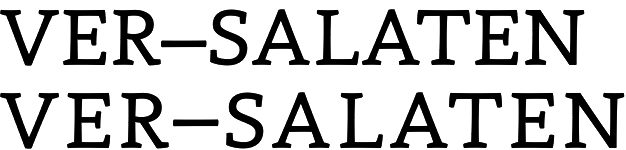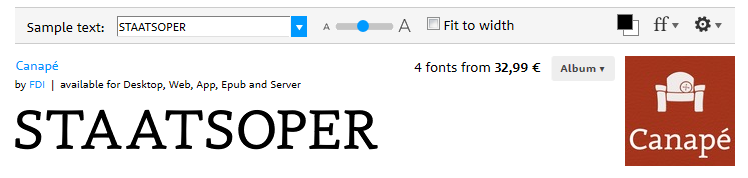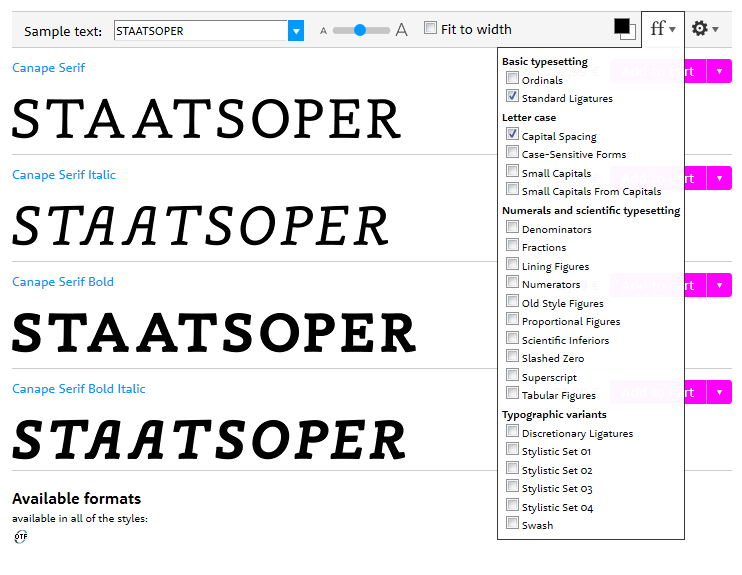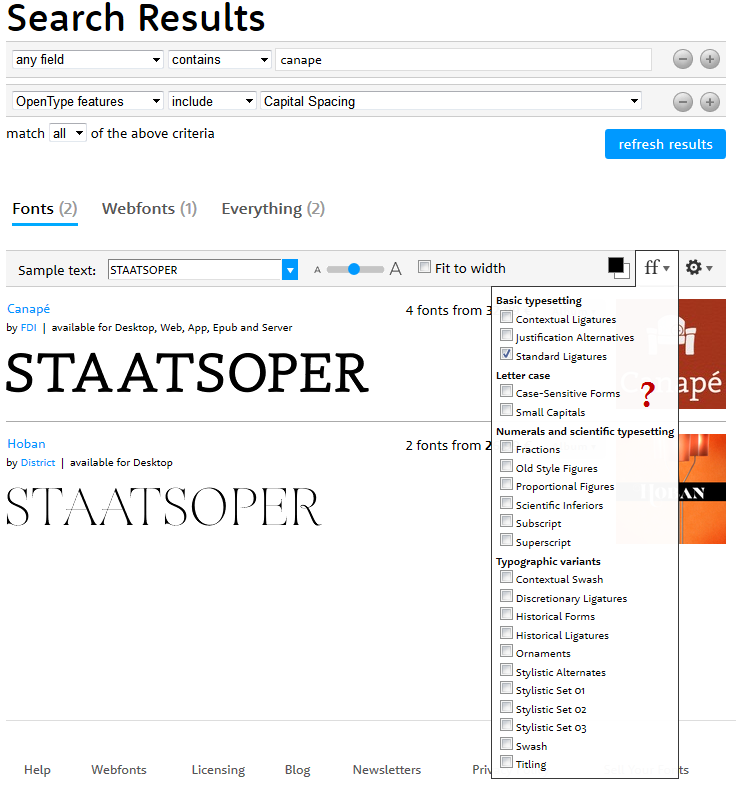
Fonts mit extra Versal-Schnitt („all caps“) – gibt’s sowas ?
Ihr werdet mir sicher zustimmen, dass das feinfühlige Ausgleichen von Versalzeilen heutzutage nahezu nirgends mehr praktiziert wird – sei es aus Nichtkönnen oder Nichtkennen. Ich habe den Eindruck, dass sich die Herren und Damen „Designer“ alltäglich damit begügen was aus dem Font herauspurzelt, wenn man Shift gedrückt hält.
Umso mehr frage ich mich, ob es bei Fonts, bzw. Fontfamilien, neben Kapitälchen-Schnitten* nicht eigentlich auch Schnitte gibt, die ausschließlich die Versalien beinhalten, dafür aber schon so zugerichtet, dass es im Allgemeinen gut ausgeglichen aussieht, wenn man damit schreibt.
Ich habe mal versucht nach so etwas Ausschau zu halten: also entweder gibt es keinen einzigen solchen Font auf diesem Planeten, oder aber mir fehlt die richtige Vokabel nach der ich suchen müsste.
Kann mir da jemand weiterhelfen?
Hättet ihr eigentlich sonst noch andere Ideen, wie man Schriftverwender in ihrer schnellebigen Alltagspraxis beim Setzen Schreiben von optisch ansprechenden Versalzeilen unterstützen könnte? Wäre es bspw. sinnvoll das als Unterschneidungspaare per OpenType-Feature in die Fonts einzubauen?
* = die leider auch viel zu oft schlecht zugerichtet, bzw. ausgeglichen sind
Die Frage impliziert, dass ein Font mit Groß- und Kleinbuchstaben nicht für Versal-Satz vorbereitet wird oder gar werden kann. Dem würde ich so nicht zustimmen. Schon ein herkömmlicher Font kann beliebige Kerning-Paare ausschließlich für Versalien bereithalten. Dazu braucht mal also keinen reinen Versalfont.
Bei OpenType-Fonts hat man dann sogar noch mehr Möglichkeiten. Hier gibt es ja bei der Umstellung auf Versalsatz ein eigenes OpenType-Feature, in dem sich die Laufweite anpassen lässt, Zeichen wie Klammern und Bindestriche verschieben lassen usw. Und das Title-Case-Feature tauscht notfalls sogar Buchstaben aus und ersetzt sie durch solche, die speziell für »Schau-Versalsatz« bestimmt sind.
Letztlich kann also jeder »gute« Font auch automatisch gut im Versalsatz aussehen. Das ist einfach eine Frage des Aufwandes, den der Typedesigner betrieben hat. Einen Spezialfont braucht man dazu nicht.
Man könnte die Frage ja umdeuten auf "welche Fonts machen sich die Mühe, Versalien nochmal für Versalsatz sauber anzugleichen, statt die Gemischtsatz-Werte zu verwenden?"
Anpassungsstufen können sein:
0) Gar nix, Versalien laufen so, wie sie für den Gemischt-Einsatz zusammen mit Minuskeln gebraucht werden
1) Versal-Kerning: Über Kerning wird sauber ausgeglichen, was aufgrund der Gemischt-Metrik ungut aussieht. Das ist viel Handarbeit, die der Schriftgestalter dem Setzer abnimmt.
2a) Opentype-CPSP-Feature "simpel gestrickt": Das CPSP-Feature addiert zu allen Versalzeichen einen festen Wert dazu (= wie Laufweitenerhöhung im Satzprogramm)
2b) Opentype-CPSP-Feature "verbessert": jedes Versalzeichen wird im CPSP-Feature gesondert betrachtet und ein passender Wert dazugegen
3) Opentype-CASE-Feature: verschiedene Satzzeichen (Klammern, Striche, ...) werden vertikal neu positioniert oder durch Sonderformen ersetzt, um besser zu Versalien zu passen.
4) Opentype-TITL-Feature: Es werden für den Titel-Versalsatz eigens gezeichnete, detailreichere Glyphen verwendet und die haben natürlich auch passende Metrik und Kerning.
Mein Canape Serif hat z.B. 1, 2a und 3 integriert, meine Tierra Nueva 1, 3 und 4.
Mal eine Verständnisfrage ...
Gibt es, wenn man es "schön" machen will, Unterschiede im Abstand für die Fälle
- durchgehender Versalsatz (VORDERRAD)
- einzelne zusammentreffende Großbuchstaben im Mischsatz? (StVO)
... hier bspw. bei VO?
Wenn gleich, könnte man ja stark vereinfacht den Platz nach links bei Großbuchstaben etwas größer machen, wie er für VO richtig passt. Dann bräuchte man nur was für die Kombi Kleinbuchstabe vor Großbuchstabe, bspw. tV oder in McIrgendwasm wo man dann ggfs. global (wenn das geht in OT?) den Zusatz wieder abzieht ...
Dann sähe das bei nicht-OT-fähigen Programmen meistens "schön" aus, außer für die wohl selteneren tV & Co.?
Dann sähe es in nicht OT-Programmen an der Linken Kante des Satzspiegels nicht schön aus, da dann alle Worte, die mit großen Buchstaben beginnen dann eingerückt sind.
Wie Catfonts schon sagt: an der Vorbreite zu spielen bringt Nachteile mit sich: linke Satzkante, Wortabstände, umgekehrter Gemischt-Satz ... das alles wieder ausgleichen – soweit es möglich ist – macht auch Arbeit und bringt Fehleranfälligkeit mit sich.
Ist StVO und STRASSENVERKEHRSORDNUNG was anders?   Ja, das erste muss sich im Minuskelsatz optisch wohlfühlen, die gedrängten Versalien sind da zu wenige zum zusammenzuklumpen. Bei letzterem hängen die Versalien (Gemischtsatz-Metrik-bedingt) zu nah aufeinanander, etwas Laufweitenerhöhung hilft hier der Formerkennung und Lesbarkeit.
Gleichzeitig sind natürlich nicht viele Fonts vorhanden, die das Feature eingebaut haben, wenn es keine Software gibt, die es nutzt ... das Henne-Ei-Problem.
CS6!
Der Versaltext war nicht manuell gesetzt, sondern über das Indesign-Feld TT (Versalien).
Nur ein Buchstabenpaar (LV) des Titels mit 14 Buchstaben ist gekernt (ungleich 0 im Kerning-Feld).
Es macht aber keinen Unterschied: Manuell gesetzt funktioniert dieses eine Paar genauso.